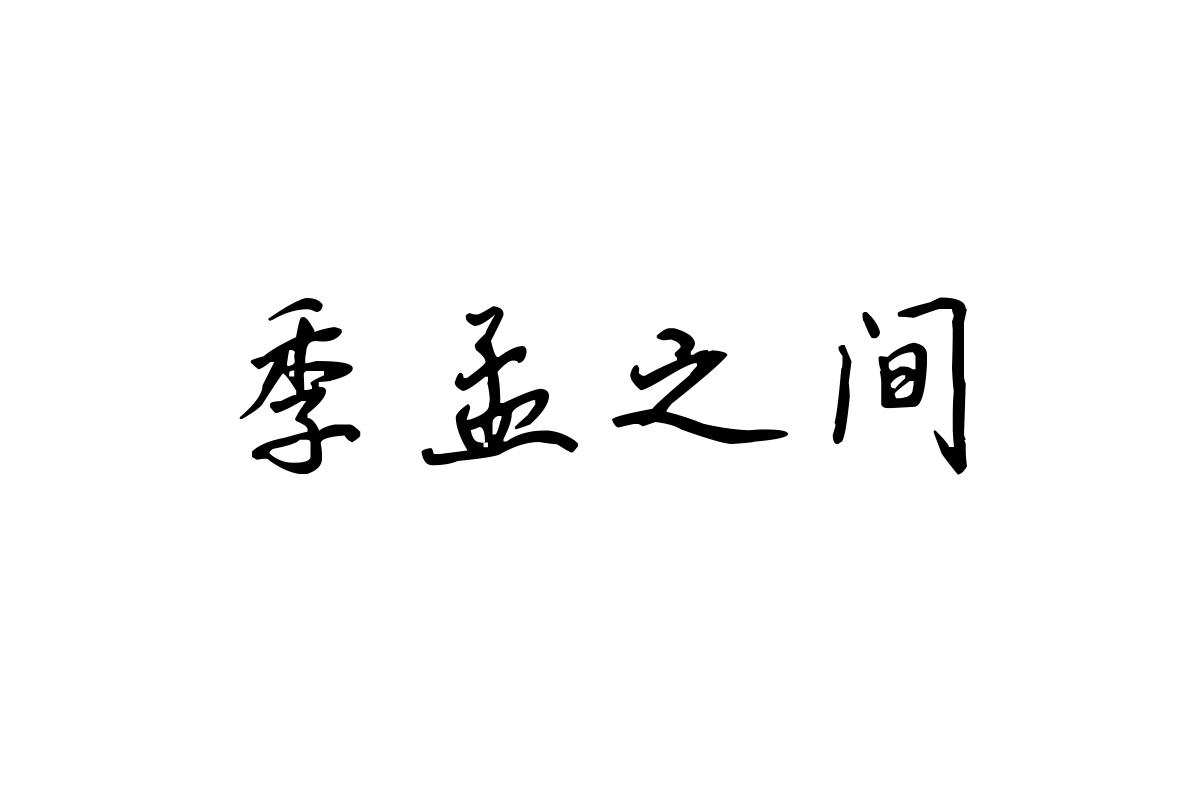
汉呈波波硬行字体是一款具有现代感的中文字体,适用于各种商业和设计项目。该字体的特点包括:
1. 字形清晰:汉呈波波硬行字体的字形线条流畅,笔画粗细适中,易于阅读和识别。
2. 结构紧凑:该字体的结构紧凑,字形大小一致,使得整体视觉效果更加协调。
3. 风格独特:汉呈波波硬行字体的风格独特,线条硬朗有力,给人一种强烈的视觉冲击力。
4. 适用范围广:该字体适用于各种商业和设计项目,如广告、海报、标识等。
总之,汉呈波波硬行字体是一款功能强大且实用的中文字体,适合用于各种需要清晰易读的场合。